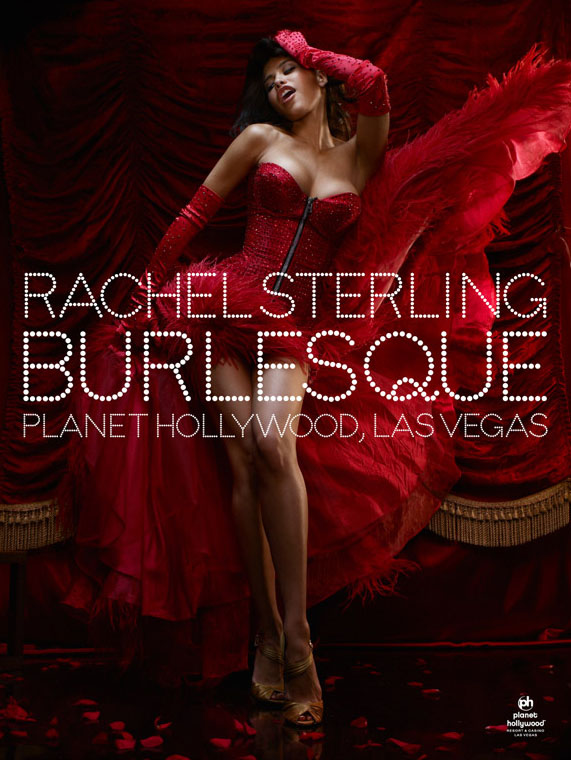
Alternativen zur Superpois gesucht!
Ich suche Alternativen zur Superpois. Also Schriften die sich aus Punkten zusammensetzen jedoch nicht einem Raster wie beispielsweise die Dot Matrix folgen.
Also eher wie die Stag Dot oder die hier im Bild gezeigte - von der ich leider nicht weiß wie sie heißt!
die Typo auf dem Plakat trifft es momentan am besten.
Jetzt muss ich nur noch herausbekommen wie sie
heißt ...
Ist das die Superpois auf dem planet hollywood poster?
diese läuft nämlich wesentlich breiter und wäre genau das, nachdem ich gerade suche. : )
kann mir wer sagen, wie dieser Font heißt?
Mit 33 Schnitten sehr variantenreich und noch dazu kostenlos die BPdots. Allerdings sind die Umlaute etwas gewöhnungsbedürftig.
Sehe gerade, daß ich überlesen habe, daß die Schrift keinem Raster folgen soll :neenee: